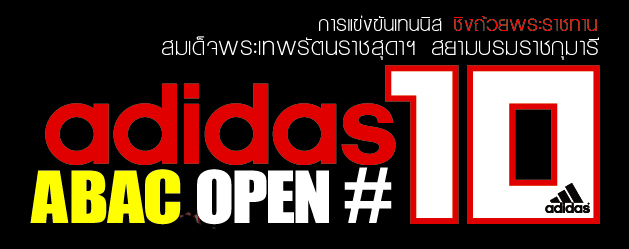
:+:ยืมหน่อยเด้อ :+:
เพื่อนมันไปเปิดร้านเช้าหนังสือ ที่กบินทร์บุรี
เลยให้ทำโลโก้ของร้านให้ ชื่อร้านว่า สบาย
แล้วมันชอบหมา ก็เลยขอมีหมาด้วย 1 ตัว
ผลออกมาเป็นดังภาพ เพื่อนฝากชมมาครับ
ว่าฟ๐นต์นี้......ดี  :22:
เอามาคืนด้วยเด้อ :22:
เอาไปให้หมดทั้งตระกูลเลยครับ
โลกนี้จะได้ถูกยึดครองโดยพี่แอนซะที
แต่ตรายางใช้อีกฟ๐นต์เด้อ  :42:
โห
เหมือนเด็กตัดกระดาษ
ตัดกระดาษ......ดองเป็นชาติ :22:
แอบรู้สึกว่า น่าจะใช้ฟอนต์เดียวกัน จะได้เป็น identity เดียวกันทั้งร้าน
ยืมหน่อยเด้อ  :22:
สองบรรทัดแรกผมจำชื่อฟ๐นต์ไม่ได้
ส่วนเบอร์ 10 ฟ๐นต์ของแอนครับ
แม้เพียงตัวเลข ก็ยังใช้ของพี่แอน  :05: :05: :39: :39: :39:
ผมว่าเขียนเองยังสวยกว่าอีก เลข 10 น่ะ  :34:
มีฟ๐นต์ของใครมั่งก็ไม่รู้ล่ะ มั่วๆ กันไป  :22: